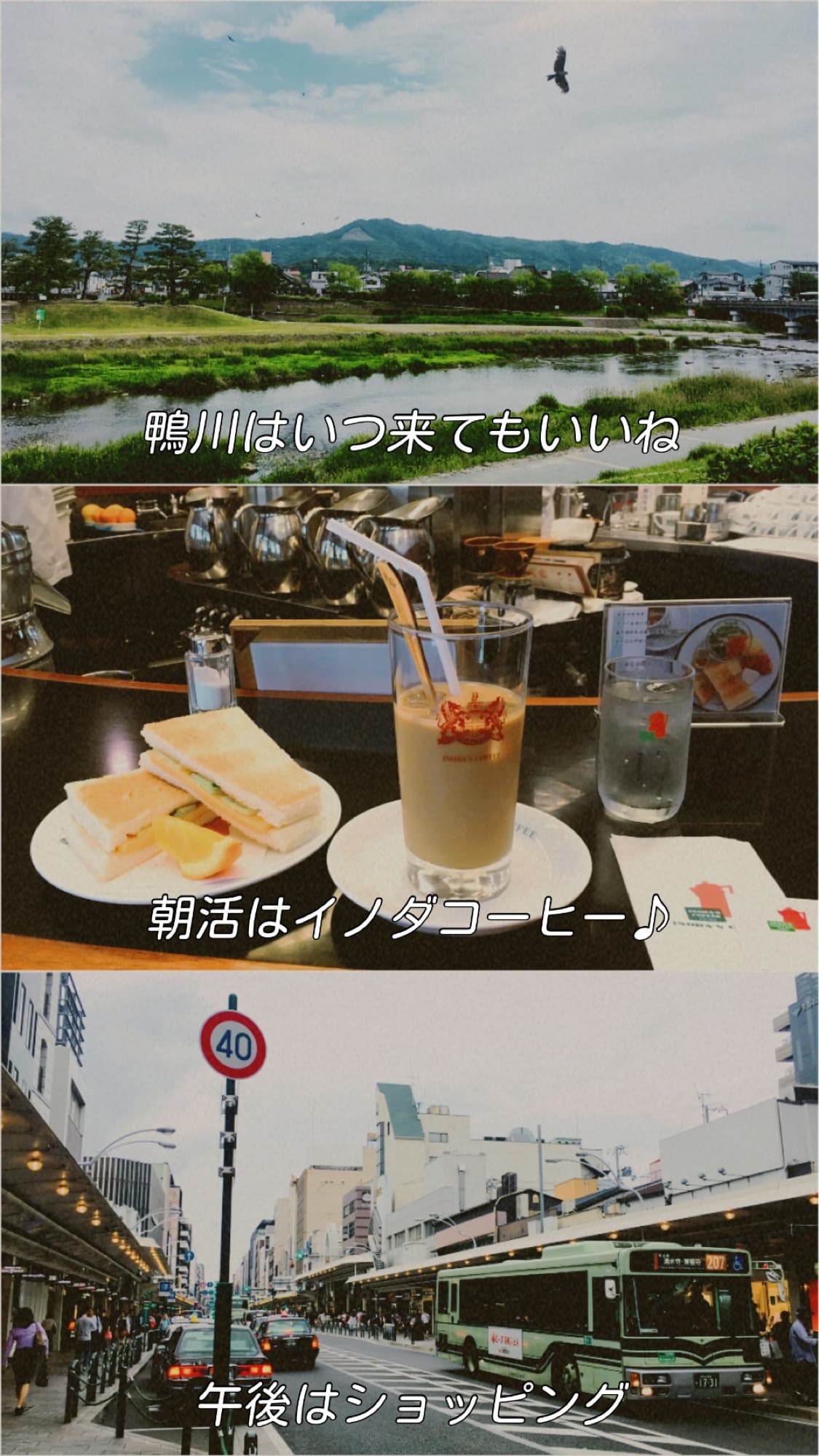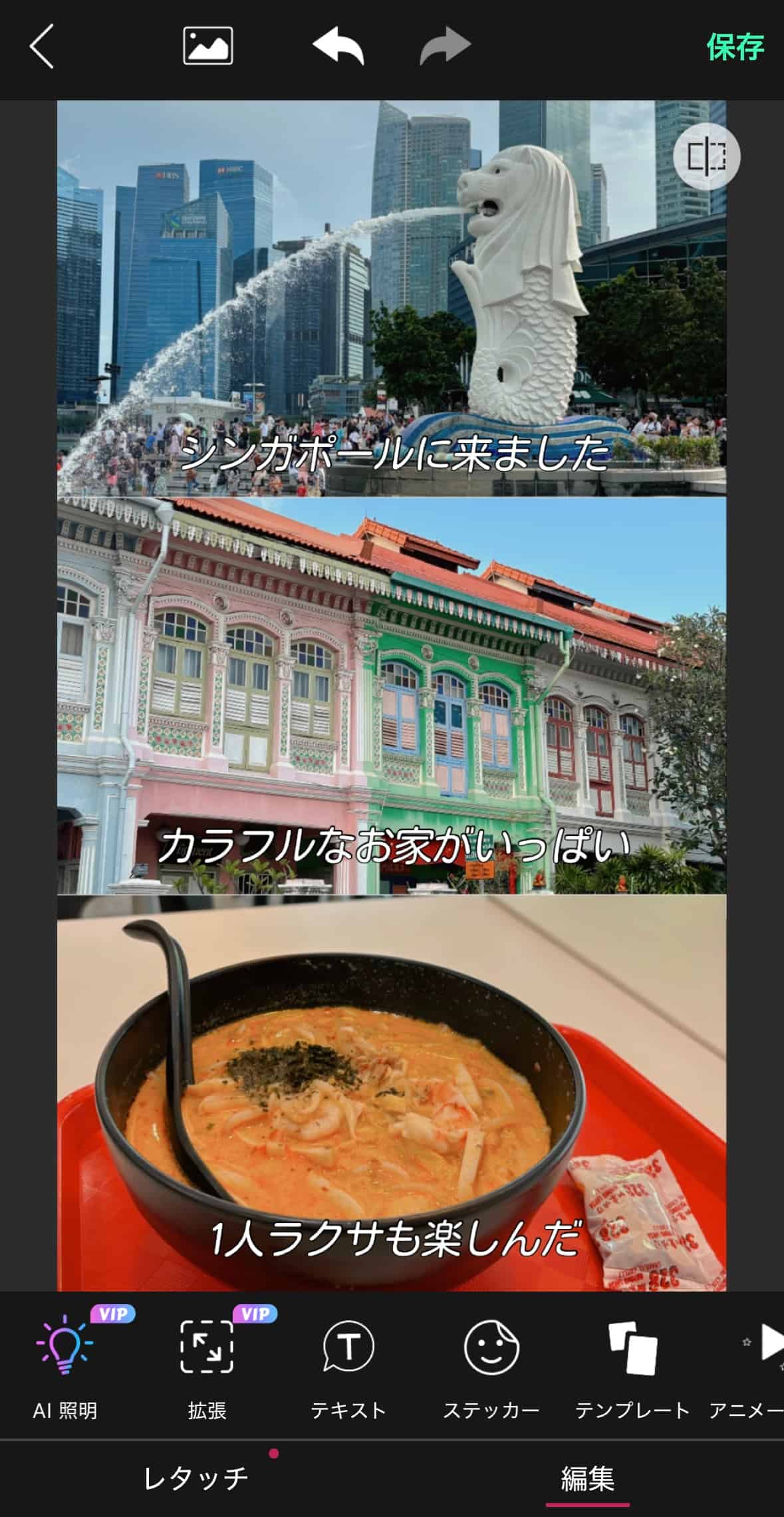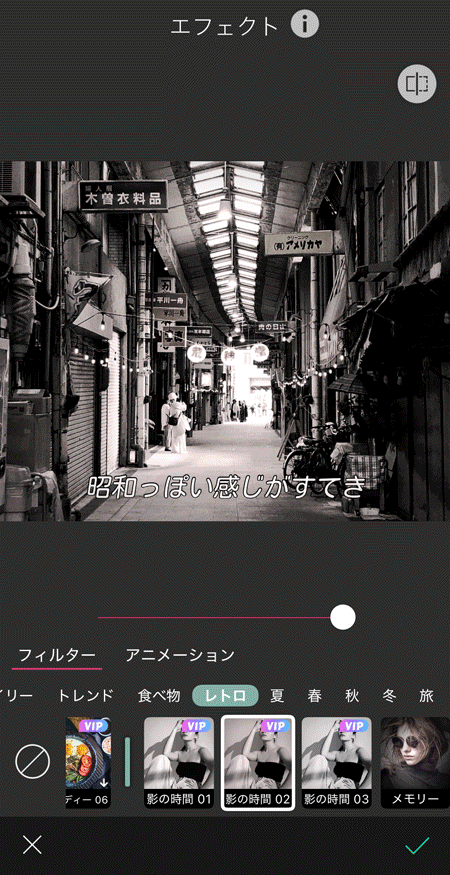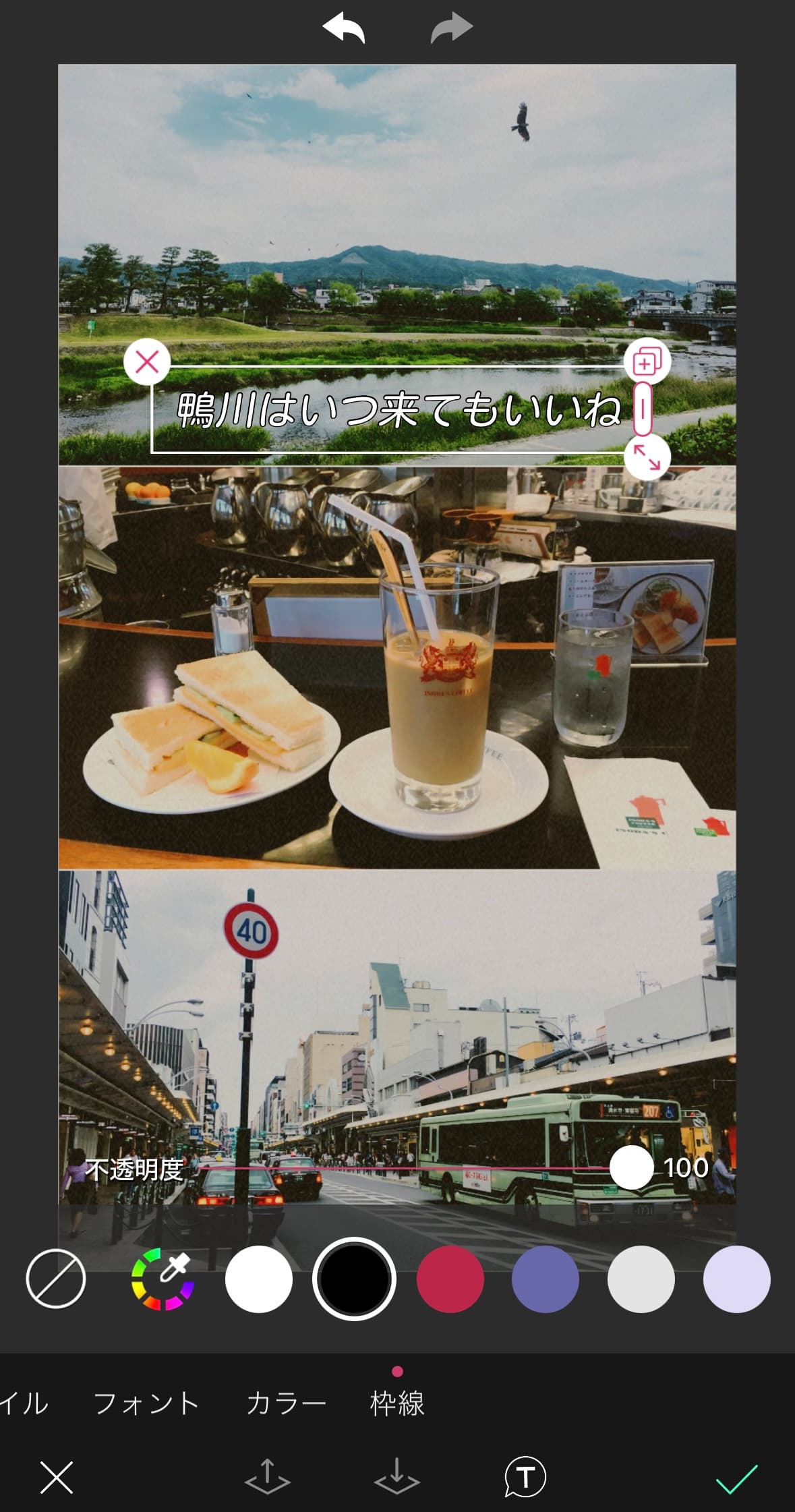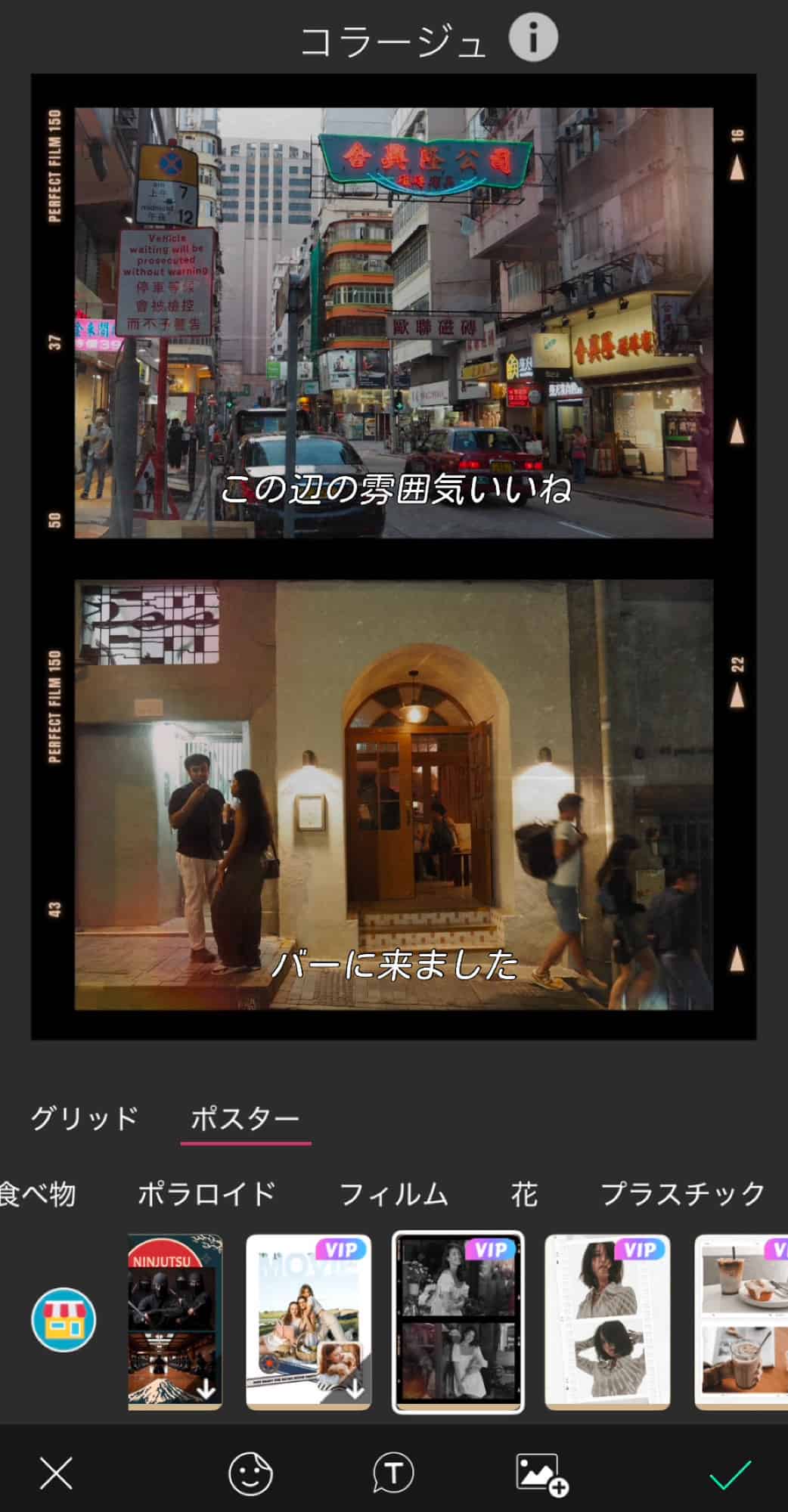
今、おしゃれなZ世代の間では、コラージュした写真に映画風のフォントで文字入れする加工がじわじわと人気急上昇中。
▲話題の映画風字幕フォント加工
実はこの加工、写真に文字入れできるアプリを使えば、簡単にできちゃうんです。
そこで今回の記事では、アプリで写真を映画風の字幕フォント加工する方法をご紹介します。
映画風の字幕フォント加工とは
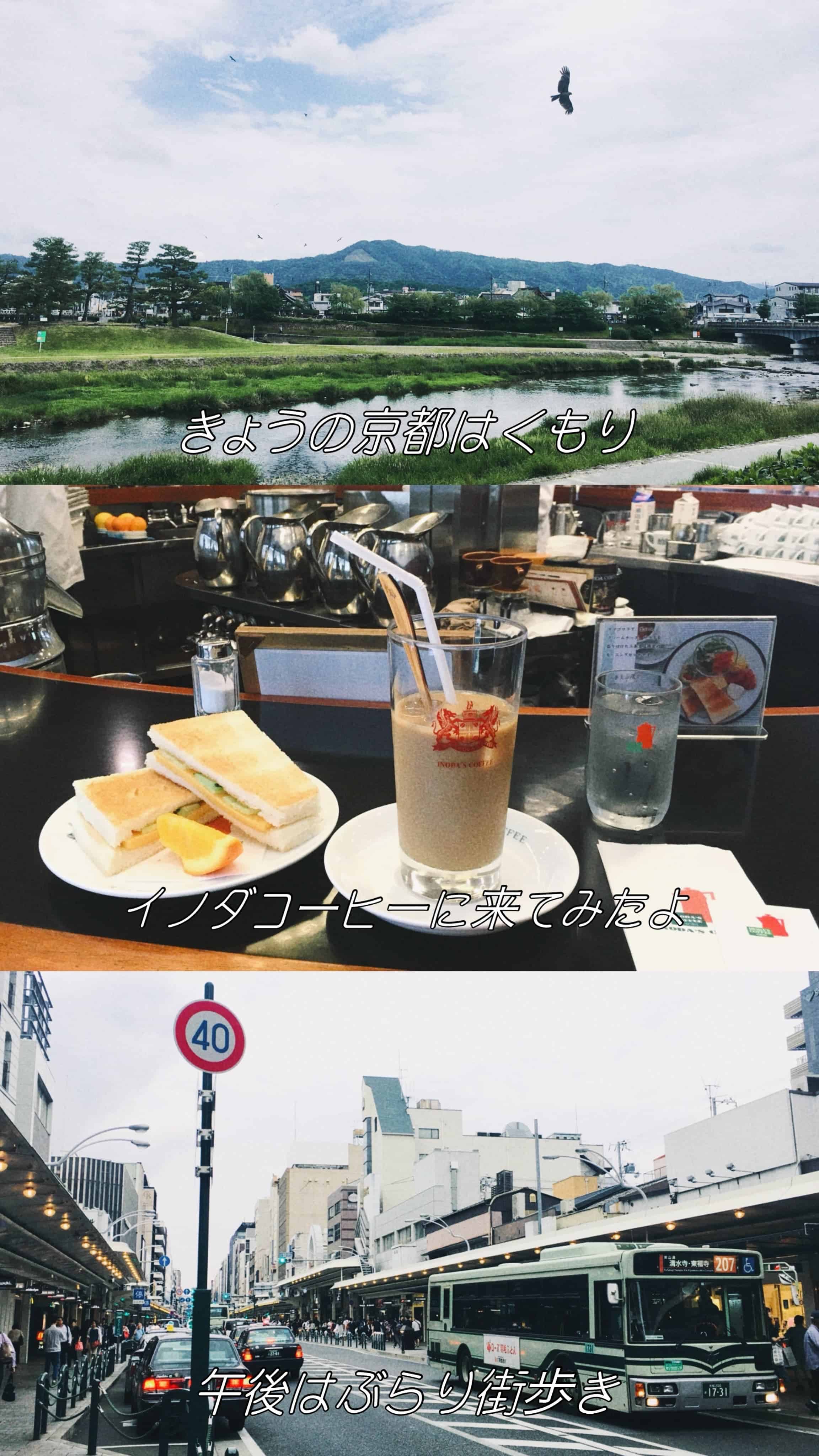
SNSで話題の映画風の字幕フォント加工とは、縦に並べた3枚の写真に、映画でよく見かける黒枠白文字デザインのフォントを入れて、シネマティックに見せる加工のことです。
このフォントをいれるだけで、何気なく撮った日常の写真にストーリー性を持たせることができるので、インスタに投稿するのにもぴったりです。
映画風の字幕フォントで写真を加工する方法
映画風の字幕フォント加工は、写真加工アプリ『ユーカム(YouCam Perfect)』で簡単にできます。
このアプリを使えば、例えばこんなに素敵な映画風字幕フォント加工ができますよ。
🎬いろいろな映画風字幕フォントを選べる
▲豊富な映画風字幕フォント
このアプリでは、映画風の字幕フォントなど、日本語だけでも40種類のフォントで写真に文字を入れることができます。
丸みのあるゴシック体やレトロな明朝体、手書き風のシネマフォントなど、写真の雰囲気別にフォントを変えてみても面白いです。
🎬映画風のフレームをつけて字幕加工を本格的に
▲映画風のフレームでもっとおしゃれに
シンプルな3分割フレームもかわいいですが、このアプリでは映画風の字幕フォントと合わせて使うとおしゃれな映画風のフレームもたくさん用意されています。
フレームをつけるだけでシネマ気分がぐっと上がります。
🎬字幕フォントにぴったりの映画風フィルター
▲日常が映画のワンシーンに
フィルター機能を使えば、字幕フォント加工用の写真を
- 無彩色のコントラストが美しい「白黒映画」
- 淡いパステルカラーが女性らしい「フェミニンシネマ」
- ビビッドなネオンカラーが映える「香港映画」
- 淡く霞んだ空気感が特徴的な「90年代邦画」
風の1枚に変えることもできます。
写真にスクラッチやライトリークをつけると、さらに個性を出せますよ。
映画風の字幕フォント加工のやり方
ここからは、実際にアプリ『ユーカム(YouCam Perfect)』で写真を映画風に字幕フォント加工する方法をご紹介します。
ステップ①コラージュを選択
アプリ『ユーカム(YouCam Perfect)』を開き、トップ画面から【コラージュ】機能を選択します。
3枚の写真を選択します。
コラージュ機能の編集画面にたどり着いたら、【グリッド】機能の中の3分割を選択します。
【比率】>【9:16】を選びます。
【エフェクト】を選択すると、各写真に映画風のエフェクトをかけることもできます。
ご自身の好みに合わせて好きなエフェクトを選んでみてくださいね。
コラージュした写真を一旦保存したら、次に編集画面から【テキスト】ツールを選択します。
【フォント】をタップし、好きな映画風のフォントで写真に合うキャプションを入れていきます。
個人的には、「小杉丸」フォントに斜めエフェクトをかけるのがおすすめです。
仕上げに【枠線】ツールで先ほど入力した文字に黒い枠線を追加します。
この行程をいれるだけで、シネマ感が一気に増します。
最後に、全ての写真に映画風の字幕フォントを追加したら完成です。
まとめ
以上、今回の記事では、アプリで簡単にできる映画風字幕フォント加工のやり方についてご紹介しました。
黒枠+白文字の字幕を写真に入れることで、日常のワンシーンがまるで映画のワンカットのように変身します。
お気に入りの写真に、ちょっとしたストーリーやセリフを添えて、自分だけの「映画」を作ってみてくださいね。